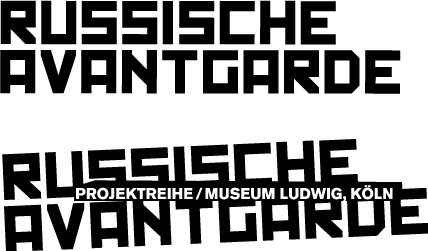
russische avantgarde
In Köln läuft eine Ausstellung zur russischen Avantgarde. Mich würde sehr interessieren, welche Schrift die für das Logo benutzt haben. Ich meine nat. die „blockige.“
Whatthefont lieferte kein Ergebnis.